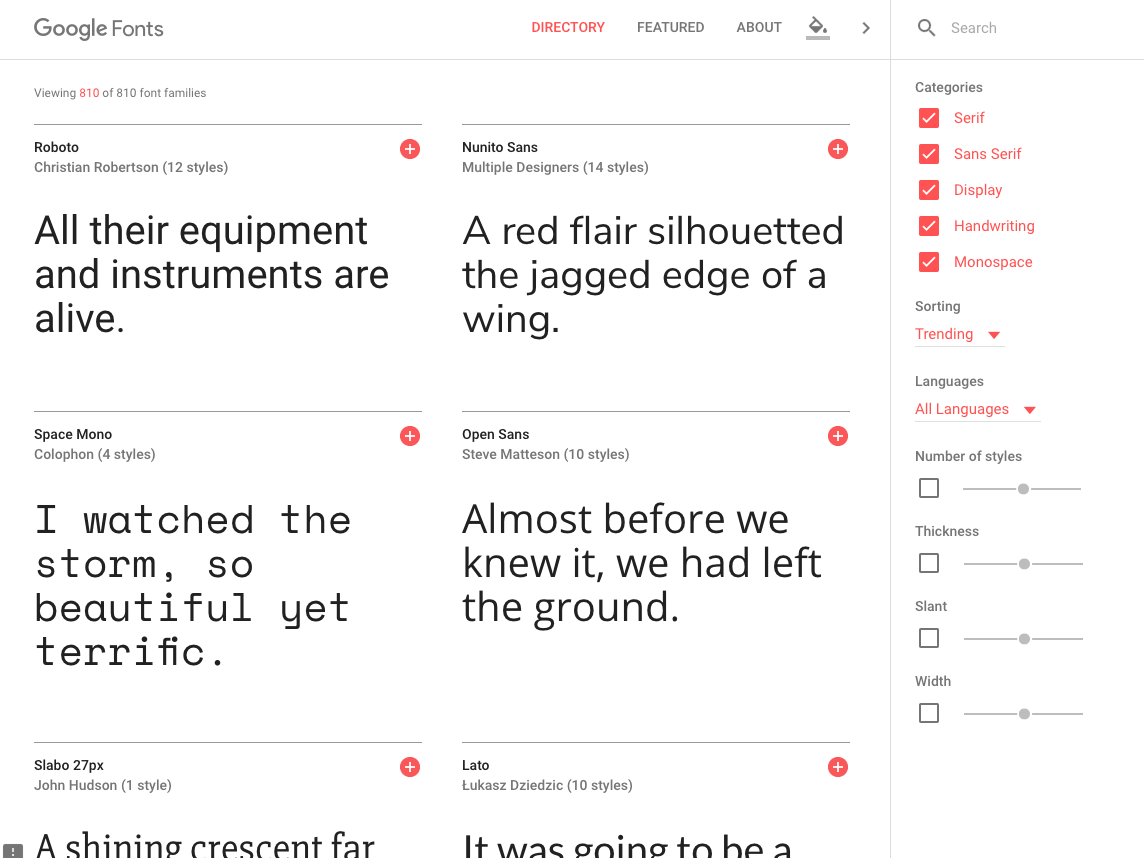
10 лучших бесплатных Google шрифтов для профессиональных презентаций • Оки Доки
Типография может сделать или сломать презентацию. Вы можете часами работать над шаблонами и цветами, но если вы выбираете нечеткие или необычные шрифты, это может повредить вашей презентации.
В профессиональной обстановке важно выбирать шрифты, которые передают чувство серьезности, оставаясь при этом игривыми. Этот баланс трудно достичь. Тем не менее, следующие бесплатные шрифты Google идеально подходят для профессиональных презентаций.
Шрифты с засечками против шрифтов без засечек
Шрифты (или шрифты) в основном делятся на две категории: с засечками и без засечек. Serif означает хвост на латыни. Шрифт с засечками — это штрихи на концах букв. Times New Roman — лучший пример популярного шрифта с засечками.
Sans означает без. Итак, шрифт без засечек — это шрифт без штрихов на концах буквы (например, Helvetica или Arial).
Для профессиональной офисной презентации лучше всего использовать шрифт без засечек.
Playfair Display — это шрифт с засечками с небольшим колоритом. Это можно проследить до эпохи Просвещения в Европе в конце 18 века, когда широкие перья были заменены острыми стальными ручками. Это дает Playfair изящный, женственный поворот. Резкий контраст со скучными шрифтами с засечками, такими как Times New Roman.
Playfair Display создает элегантный заголовок текста для презентации; особенно в сочетании с пастельным цветом фона.
Пары хорошо с: Открыть без
Arvo — это шрифт с засечками, разработанный для совершенства.
Это геометрический шрифт, который сочетает в себе классику и современность. Arvo Regular — это тонкая, современная версия с засечками, в то время как Arvo Bold имеет более толстый ход и острые углы.
Arvo Bold лучше всего подходит для больших размеров шрифта, как заголовок для бизнес или корпоративных презентаций. В сочетании с правильными цветами Arvo может быть довольно мощным.
Пары хорошо с: Лато
Вы не можете сказать это о многих шрифтах, но шрифт Crimson довольно красив. Если вы пытаетесь поразить аудиторию стильной, но веселой презентацией, подумайте об использовании Crimson для названий и субтитров.
Crimson — это шрифт без засечек, вдохновленный шрифтом Garamond, но он выходит за рамки этого. Это современный взгляд на традиционные шрифты старого стиля, разработанный с нуля, чтобы хорошо выглядеть на экранах и веб-сайтах. Если вам надоело использовать Times New Roman в презентации, переключитесь на Crimson.
Пары хорошо с: Монтсеррат
Первое правило — избегать текстовой стены. Даже список пунктов пули может быть немного слишком много. Но если вам нужна пара строк, чтобы что-то объяснить, или если вы получили длинную цитату в виде слайда, попробуйте использовать Open Sans.
Open Sans — это гуманистический шрифт без засечек с открытым исходным кодом. Это типичная рабочая лошадка шрифта, которая будет хорошо работать практически при любых обстоятельствах, когда используется текст абзаца. Это удобный разборчивый шрифт даже при небольших размерах. Полужирная версия шрифта работает так же хорошо, как и шрифт заголовка.
Пары хорошо с: Raleway
Лато означает «Лето» на польском языке, и этот шрифт действительно напоминает черновик раннего летнего ветерка. Если вы внимательно посмотрите на шрифт, то поразительно, что шрифт с таким вниманием к деталям доступен бесплатно по лицензии с открытым исходным кодом.
Лато был заказан в качестве шрифта крупной корпорацией, которая позже решила пойти в другом направлении.
Лато был затем превращен в свободный шрифт. И вы можете увидеть его корпоративные корни здесь. Шрифт игривый с его полукруглыми деталями, но все еще профессионально. Семейство шрифтов Lato довольно разнообразно, начиная с версии Hairline вплоть до Heavy и Black.
Поскольку Lato был разработан как универсальный шрифт, его можно использовать как текст абзаца, так и в качестве шрифта заголовка.
Пары хорошо с: Open Sans, Raleway
Набор Montserrat в Extra Bold — это идеальный способ передать молодость и дальновидность в профессиональной презентации. Montserrat — это шрифт, который вы часто найдете на целевых страницах технологических стартапов. Шрифт вдохновлен старыми плакатами и знаками из района Монтсеррат в Буэнос-Айресе.
Благодаря своим геометрическим формам, Montserrat является одним из тех шрифтов, который очень хорошо сочетается с другими шрифтами без засечек. Например, Montserrat в Bold будет хорошо работать с Open Sans и Lato.
Попробуйте: Используйте Roboto Slab с его кузеном Roboto практически для любого дизайна, от инфографики до визуализации данных, презентаций и маркетинговых предложений.
Учитывая, что он был создан для одноименной операционной системы Linux с открытым исходным кодом, неудивительно, что Ubuntu имеет технический, почти футуристический вид.Хотя он был создан для поддержки пользовательского интерфейса операционной системы, Ubuntu использует гораздо больше.